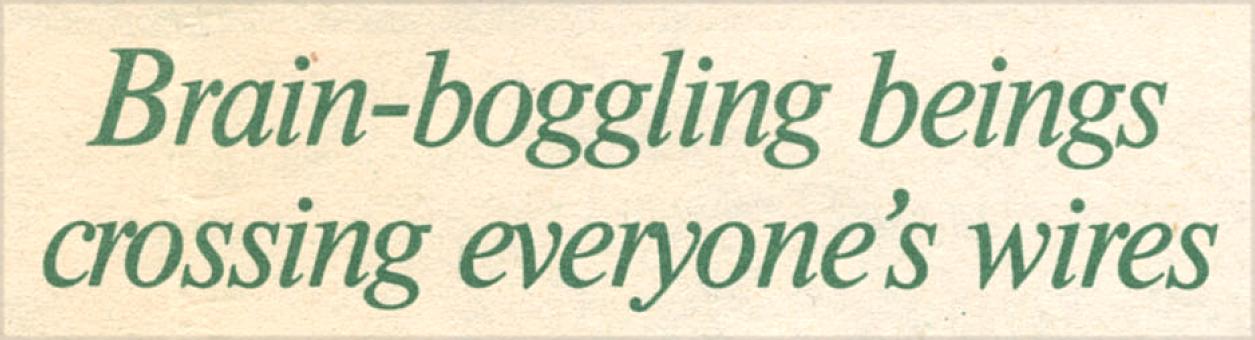
Wer kennt diese Schrift? (Brain-boggling)
Es sieht so einfach aus, aber am Ende konnte ich sie leider doch nicht identifizieren. Kann mir jemand helfen? Herzlichen Dank!
Peinlich! Ich hatte die ganze Zeit die Garamond im Verdacht, aber wohl eine falsche" Version  zum Vergleich herangezogen. Herzlichen Dank für die Hilfe und die schnelle Antwort!
Stimmt in gewisser Weise. Peinlich ist in meinen Augen die ITC Garamond und das Ausblenden der ITC Garamond aus diesem Blickwinkel durchaus verständlich. :lol:
Das ist aber auch nicht die gleiche wie oben 8-)
Aber schon sehr nahe dran. Die Garamonds, die ich mir angesehen hatte, waren offensichtlich noch weiter von der Vorlage entfernt.
Ich vermute ja, da wurde irgendwie gestaucht. Daher habe ich mal beide raus gekramt. Meinst Du nicht, dass davon eine passen könnte?
Man werfe einen Blick auf das v ;-)
Das ist Times New Roman Italic.
Das ist erst peinlich – dass wir bertel brauchen, um eine TNR zu erkennen :oops::-o
Ja, hier in München ist auch Freitag. Schwarzer Freitag. Der Tag an dem ich Times New Roman und Garamond nicht erkannte, obwohl ich sie eigentlich mit der Vorlage verglichen hatte. Puh! Hoffentlich liest das hier keiner meiner Studenten.
Ich denke wir sollten auch nach zwei Schriften suchen. Das r in der kleinen Zeile ist anders.
Wo hast Du den Spaß eigentlich her. Was sehen wir da? Gibt es Hintergrundinfos?
Warum nicht? Kommt doch ganz gut hin, soweit man das mit dem kleinen Bild und so eng gesetzt beurteilen kann :-?
Nö. Das r in »stroke« ist anders. Und das k hat definitiv nichts mit der Times gemein.
Ich behaupte also mal nach wie vor, dass auch etwas in Richtung Garamond im Spiel ist. ;-)